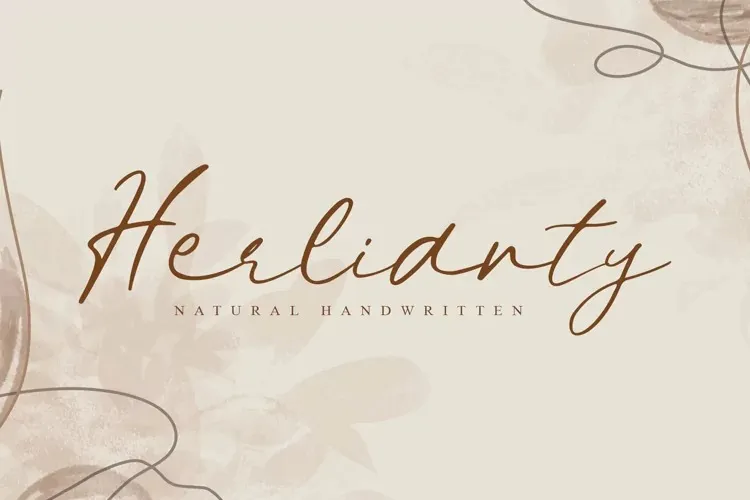
A fonte ‘Herlianty Font’ é uma proposta moderna e casual que se destaca por sua influência na escrita a mão simples dos cidadãos brasileiros, seja nos envelopes de mensagens ou notas pessoais. Suas linhas fluidas e personalizadas permitem um toque delicado em design para eventos sociais como casamentos, embalando o estilo casual sem perder a elegância. Perfeita tanto para criação de logotipos e marca, quanto para o desenvolvimento visual de produtos estilizados ou a decoração de posters, essa fonte tem um amplo campo de aplicação que abrange várias categorias de design gráfico. Seja você designer ou empresário que busca uma fonte única e versátil que se destaca, ‘Herlianty Font’ é a escolha ideal para sua necessidade.